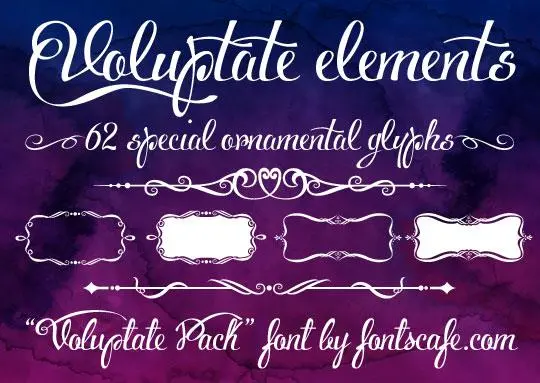
Voluptate font
Aqui está uma versão curta e envolvente das descrições para a página de download da font “Voluptate Font” escrita em português do Brasil: A font Voluptate é perfeita para quem busca um toque delicado e autêntico. Ela foi criada pelo designer Hamilton, oferecendo uma experiência única tanto na escrita quanto na leitura. As linhas elegantes e os detalhes minuciosos são características que tornam essa fonte não apenas bonita, mas também muito versátil. Se você está procurando por um recurso gráfico adorável para aplicativos digitais ou projetos de designer, Voluptate é uma escolha perfeita. Com sua natureza handwritten, ela se adapta ao seu estilo sem exigir muita atenção especial. A fonte oferece versões full e comerciais que podem ser acessadas diretamente na Fontescafé. Para quem deseja conhecer mais sobre a font Voluptate e as outras opções disponíveis, a Fontescafé é uma ótima referência. Os canais de redes sociais da empresa também são fáceis de se encontrar e seguem com notícias, novidades e promoções exclusivas para seus assinantes. Com sua delicadeza e autenticidade, Voluptate se torna a fonte perfeita para quem busca um toque especial em suas criações digitais.